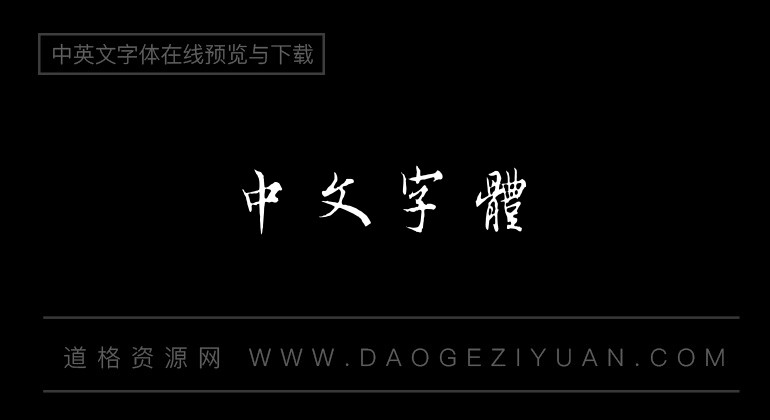
迷你繁欧行字体是一款繁体中文字体,由欧洲字体设计师米兰·瓦尔克创作。它采用了细节精细、结构清晰、比例协调的特点,融合了欧洲传统字体的精髓,以清新的表现形式呈现繁体中文的优雅和精致。迷你繁欧行字体细腻的笔画、精致的结构,以及清新的表现形式,可以很好地表达文字的艺术精髓,是一款非常适合用于设计、网页制作、文字排版等场合的字体。文件名:MiNiFanOuXing-1.ttf
迷你繁欧行是一款非常不错的手写艺术字体,具有很好的视觉感,适合于文化类的宣传设计、商业类品牌的广告和产品包装设计以及个性化文字排版等较多场景。